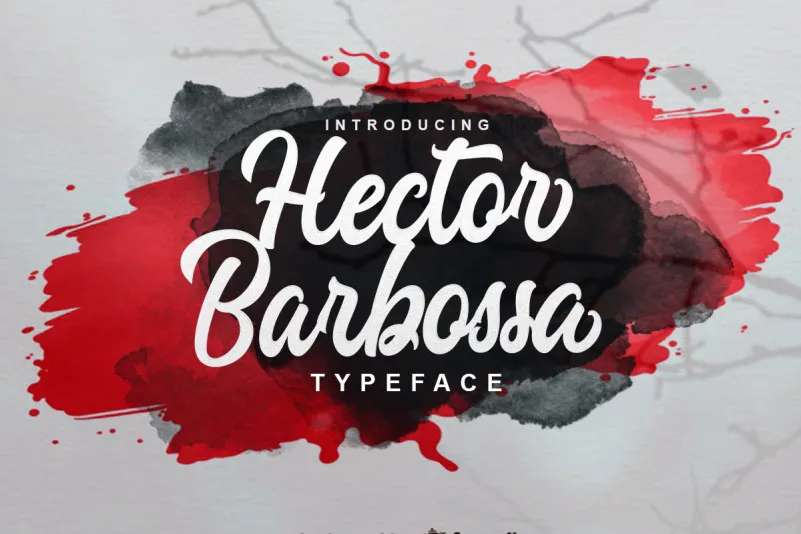
Hector Barbossa Script Font – Download Grátis
A fonte “Hector Barbossa Script Font” é ideal para quem busca criar a aparência única de mão escrita customizada. Desenvolvida pelo designer BhadalStudio, esta tipografia casual e combinada com a estilo de letra por mãos oferece um poderoso recurso para projetar qualquer marca de sua própria criação ou do seu cliente. Possui uma grande aplicabilidade em diversas áreas como logotipos, design de produtos, selos, marcas de água, postagens nas redes sociais, roupas, convites, painéis, clubes esportivos e até mesmo para carros e motocicletas. Seja você um designer ou alguém que cria arte digital com frequência, esta fonte lhe proporcionará o poder de transformar qualquer projeto em algo único e autêntico. Engajue-se na experiência de criar designs memoráveis com a “Hector Barbossa Script Font”.